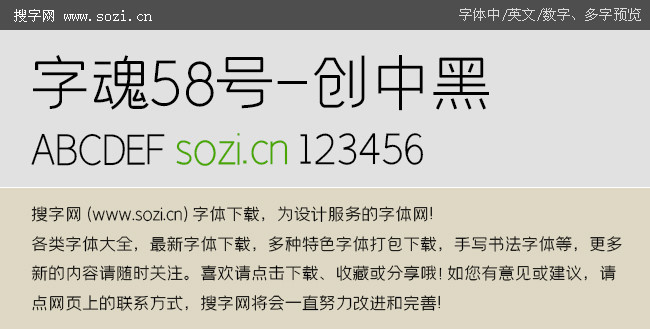
字魂58號(hào)-創(chuàng)中黑
搜字網(wǎng)提供一款字魂58號(hào)-創(chuàng)中黑中文字體下載,該字體是一款基礎(chǔ)黑體字體,該字體包含6763個(gè)中文、字母、 符號(hào)和數(shù)字,具有古典、中國(guó)風(fēng)、現(xiàn)代、優(yōu)雅、簡(jiǎn)約 的風(fēng)格,可以滿足您設(shè)計(jì)上的各種需求,該字體主要用于屏顯、印章、標(biāo)志、導(dǎo)視、健康養(yǎng)生、電商、媒體、活動(dòng) 等場(chǎng)景。